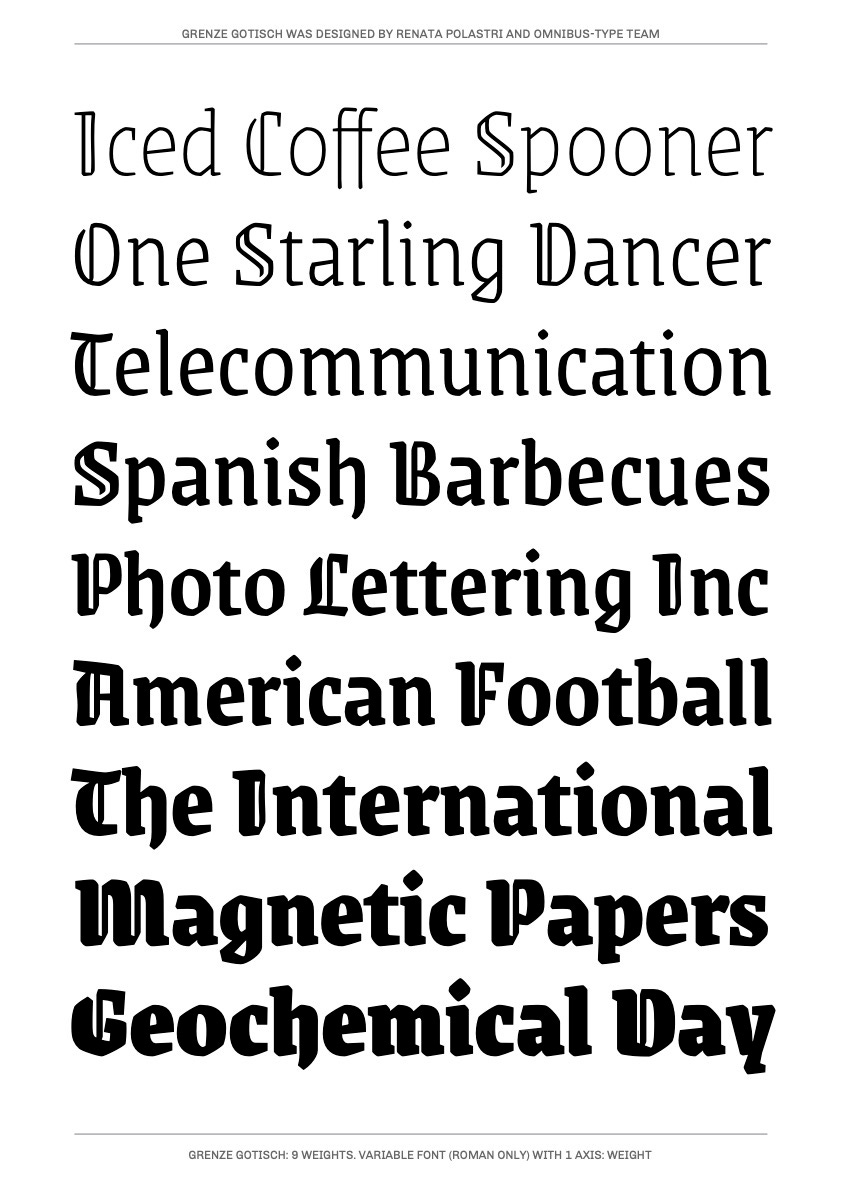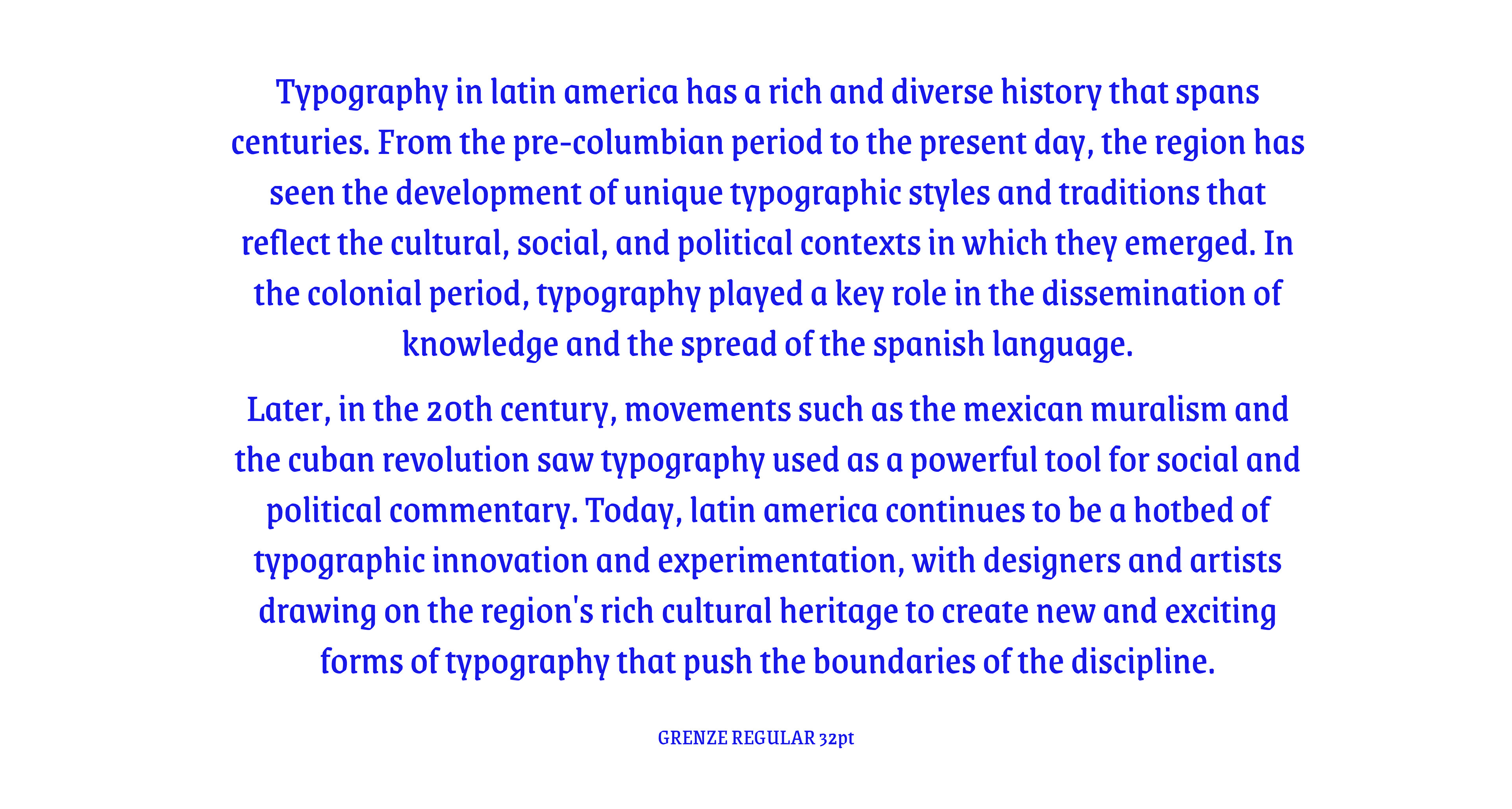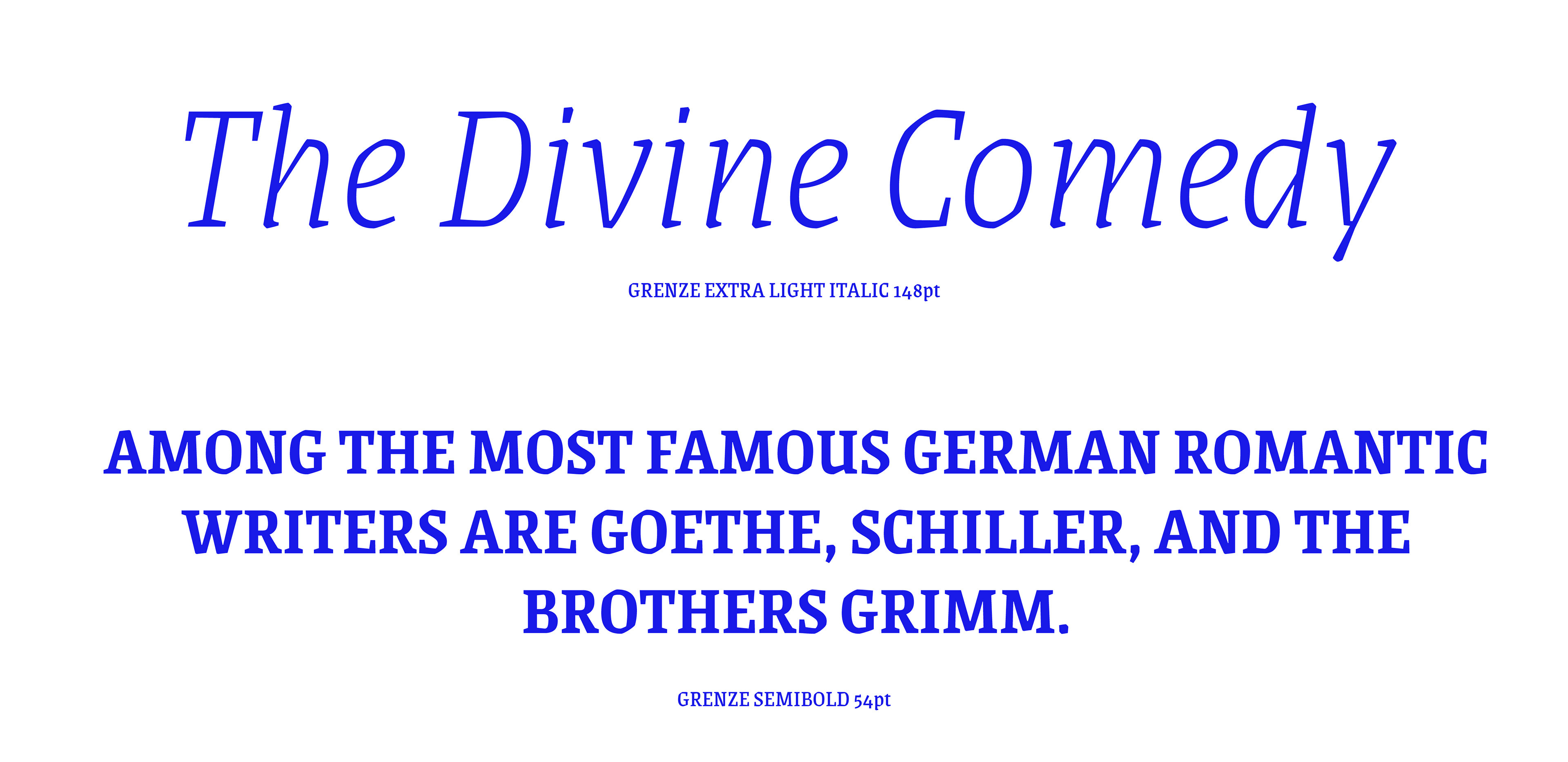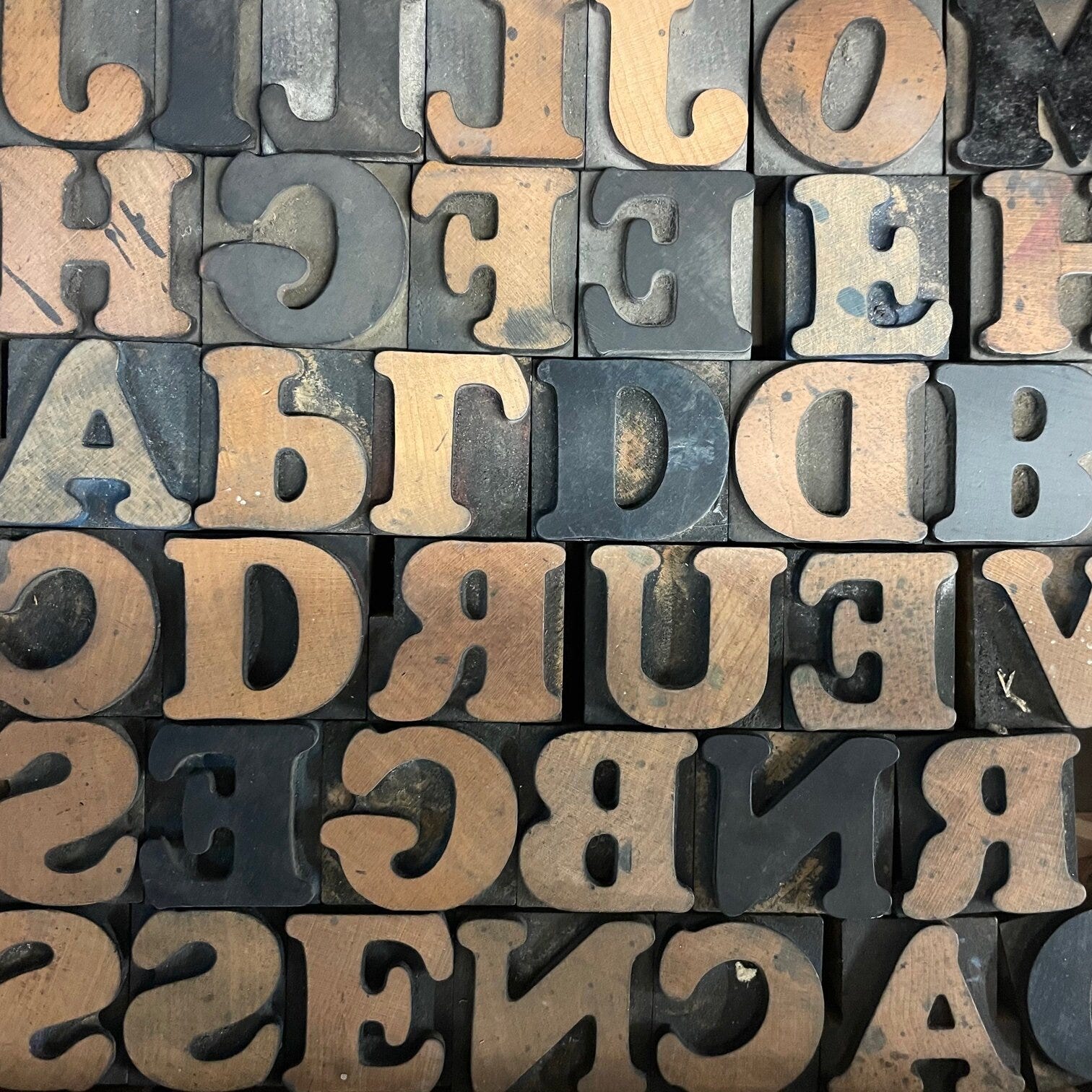
Vamos falar de fontes #3 – Cooper Black e Grenze
Manchas fofinhas e romanas góticas
Cooper Black (Barnhart Brothers & Spindler/ATF), de Oswald Bruce Cooper
Da segunda metade do séc. XIX até o crash financeiro de 1929, os EUA viveram um momento próspero em sua economia. No entanto, a indústria tipográfica estadunidense foi colocada em uma situação complicada; as máquinas de composição a quente da Linotype tomaram o mercado gráfico no país, reduzindo a demanda por tipos móveis e forçando donos de foundries a juntarem-se para proteger seu mercado. Esse contexto foi importante para o surgimento da American Type Founders, uma fusão das maiores fundidoras de tipos dos EUA que ajudou a padronizar o mercado tipográfico local e torná-lo mais competitivo contra fundidoras europeias.
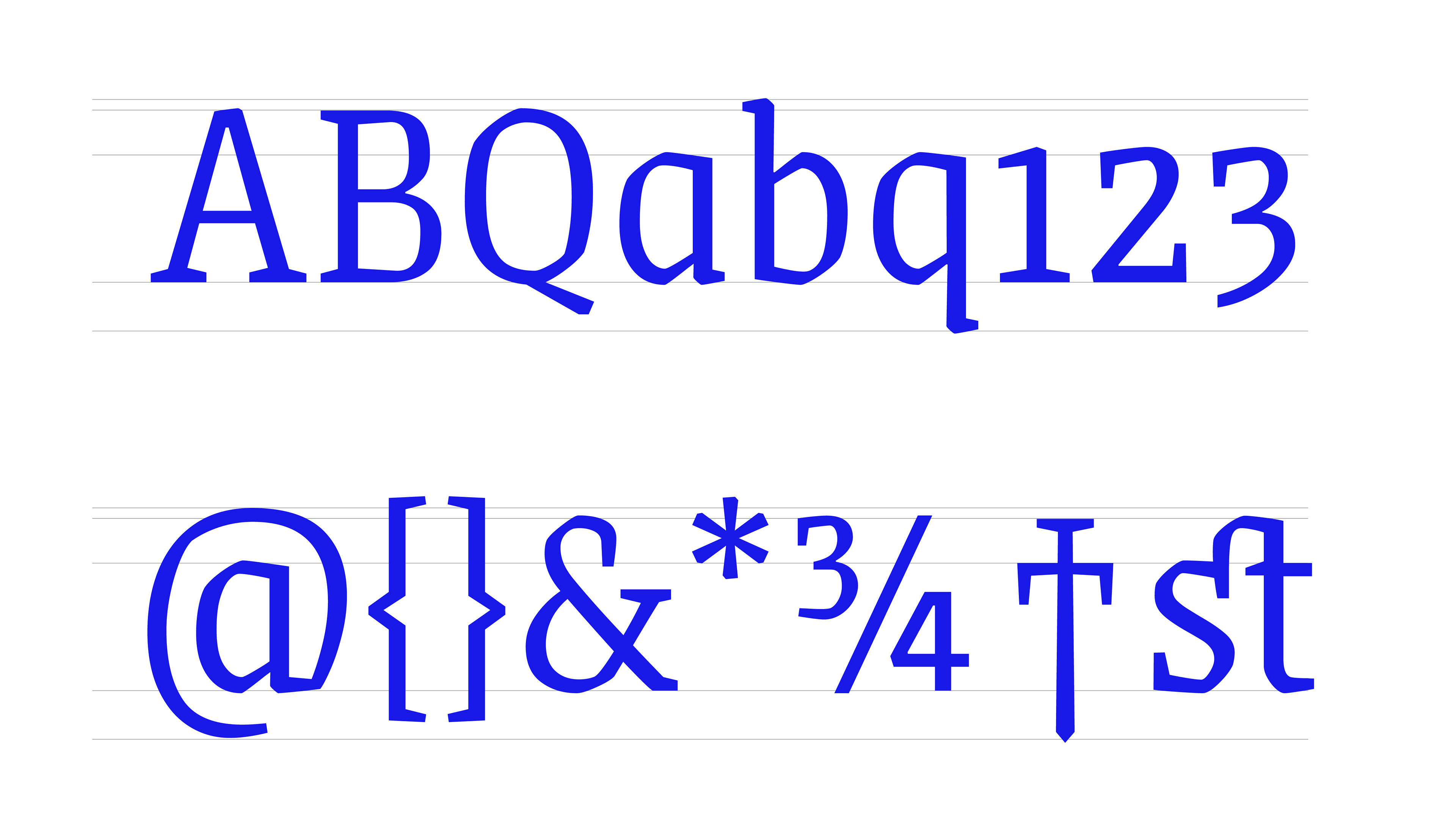
A ATF foi também uma importante plataforma para type designers americanos, que ajudaram a criar um estilo “americano” de tipografia. Dessa época, temos designers relevantes até os dias atuais, como Frederick Goudy, Morris Fuller Benton e “Oz” Cooper. Nascido numa pequena cidade de Ohio, Oswald Bruce Cooper estabeleceu-se em Chicago como letrista e administrador do maior estúdio de produção gráfica do meio-oeste americano, especializando-se em tipografia e abertura de letras. Sua reputação rendeu-lhe um convite da fundidora Barnhart Brothers & Spindler para desenhar uma família tipográfica homônima, aceito após incentivo de seu sócio Fred Bertsch, dando origem à tipografia Cooper Old Style.
Quatro anos depois, Cooper criou mais dois estilos que se tornaram sucesso de vendas e objeto de discórdia entre type designers da época. Cooper desenhou uma versão pesada de suas primeiras fontes, aumentando espessuras de traços e mantendo serifas e acabamentos arredondados. Assim, em 1922, foi lançada a família Cooper Black, com versões normal e itálica. O peso exagerado dos caracteres da Cooper Black, comparada com quaisquer fontes da época, fez ela ser mal-vista por outros colegas de profissão de Oz, que apelidaram-na de “ameaça negra”. No entanto, comparada a outras fat faces da época, o contraste reduzido e a aparência redonda fez dela um sucesso no mercado publicitário.
A partir daí, o resto é história. A Cooper Black foi incorporada ao acervo da ATF em 1933, com a aquisição da Barnhart Brothers & Spindler, e tornou-se um ícone do design gráfico com o tempo. Ela está presente em grandes álbuns do rock, como L.A. Woman (The Doors), Pet Sounds (Beach Boys) e The Rise and Fall of Ziggy Stardust and the Spiders from Mars (David Bowie). Ainda na música, o hip-hop adotou a Cooper Black em capas de álbuns e no vestuário customizado de rappers e MC’s durante os anos 1970 e 1980. A Cooper Black esteve também em séries de TV e streaming, como Everybody Hates Chris (2005—2009) e Dear White People (2017—2021).
Ela também aparece em algumas identidades visuais, como a da companhia aérea easyJet, dos alimentos Uncle Bens, da rede canadense de vestuário Roots, entre outras empresas. Sua aparência amigável e “fofinha” fazem com que, mesmo apresentando um grande peso visual, seus caracteres despertem simpatia. A versão itálica parece ainda mais cool e despojada, dando uma sensação de movimento e rapidez às letras pesadas de Oz. Essas qualidades fizeram da Cooper Black a segunda fonte mais vendida da história da ATF. A associação, por sua vez, não teve uma história tão longa, encerrando suas atividades ao ter sua falência decretada em 1993; contudo, o esforço que fez para que seus type designers fizessem frente às fundidoras europeias ajudou a Cooper Black a marcar seu espaço no design gráfico e manter-se influente até hoje.
Grenze (Omnibus Type), de Renata Polastri
Quando estudamos a história da tipografia, vemos Johannes Gutenberg desenvolvendo sua prensa de tipos móveis entre 1448 e 1450, e criando tipos baseados nas letras blackletter, usadas pelos calígrafos alemães da época. No entanto, ao aterrissar na Itália, o estilo blackletter foi rapidamente substituído pelo que entendemos atualmente como tipos romanos, inspirados nas antigas capitais imperiais romanas e na caligrafia humanista feita por letristas locais. Essa transição, influenciada pelo Renascimento, é importante para consolidar as formas das letras que usamos atualmente, mas é pouco explicada para alunos de design, e até mesmo profissionais da área têm dificuldade de entender esse momento histórico.
Conforme a tecnologia das oficinas tipográficas espalhou-se pela Europa, o modelo de letras criado na Itália também tornou-se padrão na França, Flandres, Países Baixos, Península Ibérica e leste europeu. O estilo blackletter ficou recluso, servindo de modelo para alguns tipos gravados ao longo do tempo. O uso pelo partido nazista em sua comunicação oficial, entre as décadas de 1930 e 1940, colocou as letras pesadas de formas retas no ostracismo novamente. O blackletter reapareceu, aos poucos, por meio da contracultura, do heavy metal e do hip-hop; o trabalho de resgate histórico feito por Rudolf Koch na Alemanha dos anos 1920 serviu de base para que o blackletter ganhasse uma nova vida entre calígrafos e artistas de lettering contemporâneos.
Na tipografia, o estilo blackletter é uma referência para designers, tanto em revivals de modelos históricos (especialmente o subgênero Fraktur) quanto em fontes autorais, que usam seu aspecto modular e quadrado como referências em novos desenhos de tipos. Alguns produtos dessa influência do blackletter incluem fontes com inspiração mais óbvia, como a Bork de Lu Leitenperger, nascida com o desafio de fazer uma fonte usando apenas pontos sem curvas de bézier. Outras fontes monstram uma influência do blackletter em outras vias, como é o caso da Grenze, da designer Renata Polastri.
Desenvolvida entre 2016 e 2017, a Grenze não é categorizada como uma família tipográfica blackletter a princípio, apresentando as formas tradicionais dos tipos romanos. A influência das letras “góticas” aparece quando olhamos seus caracteres mais de perto e vemos, por exemplo, alguns traços “quebrados”, como se a pena quadrada viajasse por um ductus que muda de direção abruptamente. Esse aspecto “quebrado” guarda semelhança com o aspecto quadrado das letras blackletter. As inclinações presentes nas serifas e nas porções inferiores de letras como “c”, “e” e “o”, que evocam as terminações inferiores em diamante de estilos como a textura quadrata. Estes e outros atributos justificam a Grenze como um “híbrido” entre as letras romanas tradicionais e o blackletter.
A alta qualidade das letras desenhadas pela Renata fez com que a Grenze fosse selecionada para a 8ª Bienal do Tipos Latinos, em 2018. A fonte possui uma variação chanada Grenze Gotisch, cujas letras maiúsculas possuem traços decorativos com inspiração mais clara nas letras blackletter, assim como as terminações prolongadas de caracteres como “h” e “f”. Distribuída sob a SIL Open Font License, a Grenze está disponível para uso gratuito tanto na plataforma Google Fonts quanto no portal da Omnibus-Type. Tipografias como a Grenze, Bork e outras mostram como um estilo pode ser resgatado e interpretado de diferentes formas, gerando resultados inovadores baseados na mais antiga das tipografias europeias.